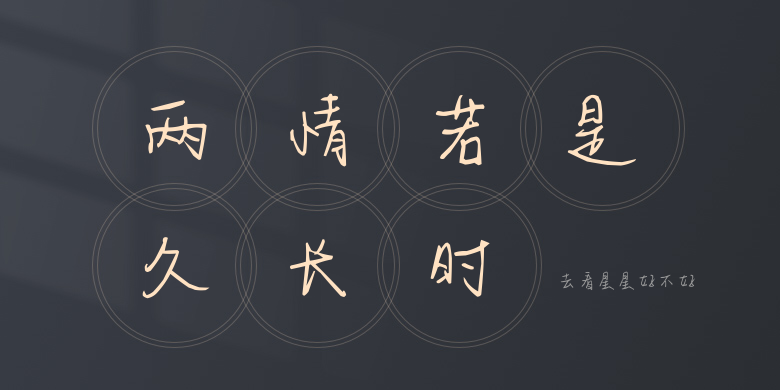
去看星星好不好
去看星星好不好,这款字体结构工整、笔画清晰,兼顾美观与易读性,适用于标题、正文、海报、包装、LOGO 等多种场景。字形优雅稳定,风格百搭耐看,适配日常排版与创意设计,让文字呈现更舒适、更具质感。去看星星好不好一笔一画,皆是细节,以均衡的比例、流畅的线条打造舒适视觉体验,字形端正大气,风格简约现代。无论是商业设计、品牌宣传还是日常排版,都能轻松驾驭,让文字更有格调与力量。去看星星好不好字体下载。